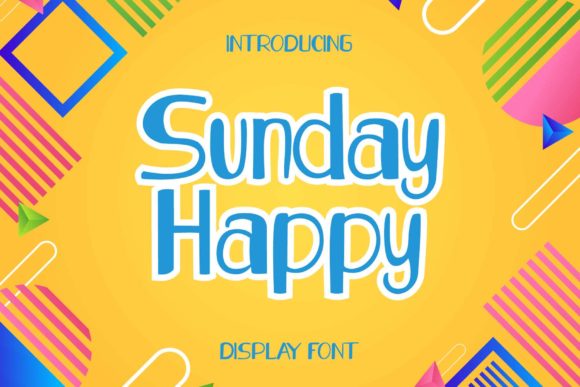
Sunday Happy - это радостный и милый шрифт.
Благодаря своей простоте, он подходит для невероятно широкого спектра дизайнов, поэтому смело добавляйте его и замечайте, как оживают ваши идеи!